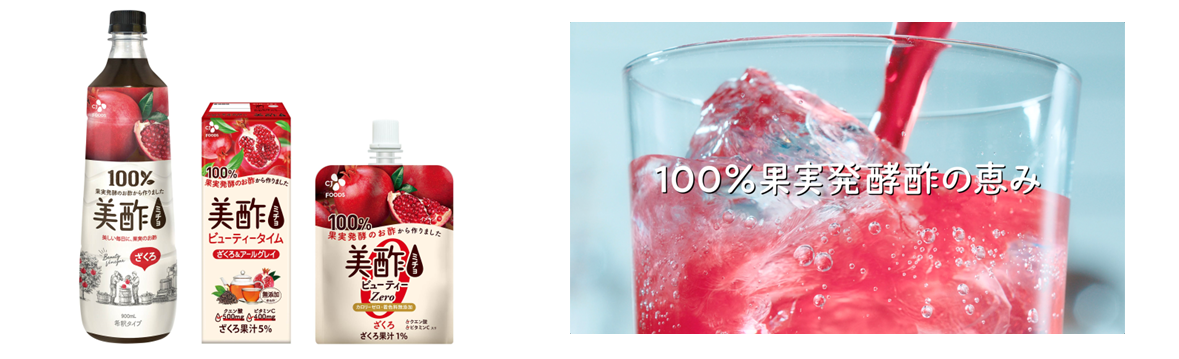
モリサワがビネガードリンク「美酢」ブランドのオリジナルフォントを開発
モリサワはCJ FOODS JAPANのビネガードリンクブランド「美酢(ミチョ)」のリブランディングプロジェクトの一環としてオリジナルフォント「CJ MICHO」を共同開発したことを2023年9月8日に発表した。
CJ FOODS JAPANは、韓国の代表的な調味料「ダシダ」など食品事業を展開しており、「美酢」は100%果実発酵酢から作ったビネガードリンクブランドとなる。日本における美酢の発売開始から10年を機にリブランディングのプロジェクトを始動し、CJグループとして初めてとなる日本語のブランドオリジナルフォントを開発した。
今回開発したオリジナルフォントは、ロゴや商品パッケージのほか、映像、Webまで幅広く使用される予定のため、ブランドイメージを象徴するデザインながら、視認性や汎用性も重視し、使用頻度の高い漢字・ひらがな・カタカナと記号の計135文字を開発した。
オリジナルフォント「CJ MICHO」は、すでにテレビCMに採用され、順次、商品パッケージにも展開が予定されている。
▼現行の商品パッケージ。新フォントはこれから展開予定(左) 新フォントが採用されたテレビCMのワンシーン(右)